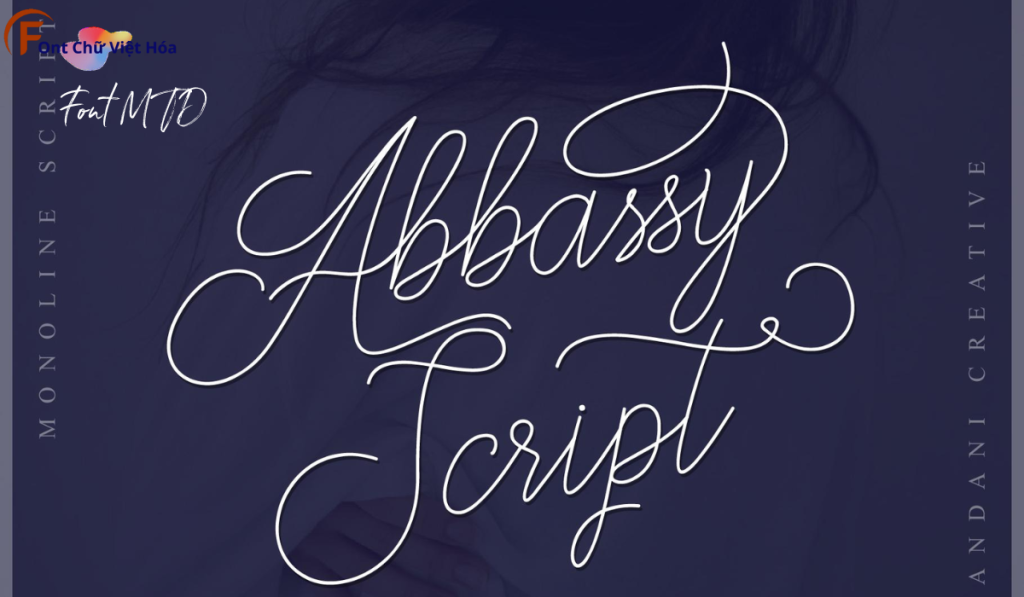
Font MTD Abbassy Script Việt Hóa
Phân loại: Hiện đại, tinh tế
Kiểu chữ: Script
Font MTD Abbassy Script Việt Hóa, thuộc bộ font MTD, mang phong cách viết tay mềm mại và tinh tế, phù hợp cho các dự án thiết kế như thiệp mời, bìa sách, và các sản phẩm thủ công. Với các nét chữ uyển chuyển và độ dày đều đặn, Font MTD Abbassy Script Việt Hóa không chỉ dễ đọc mà còn tạo cảm giác nghệ thuật và thanh lịch. Việc Việt hóa font giúp người dùng dễ dàng tích hợp vào các thiết kế tiếng Việt, mang lại sự tiện lợi và nâng cao tính thẩm mỹ.